Ägyptische Schriften
Am Ufer des Nils entstand eine der ältesten und bildreichsten Schriftkulturen der Welt. Von den feierlichen Hieroglyphen auf Tempelwänden über das fließende Hieratisch der Priester bis zum schnellen Demotisch des Alltags — drei Schriften für drei Zwecke.
Am Nil
Bilder werden zu Buchstaben
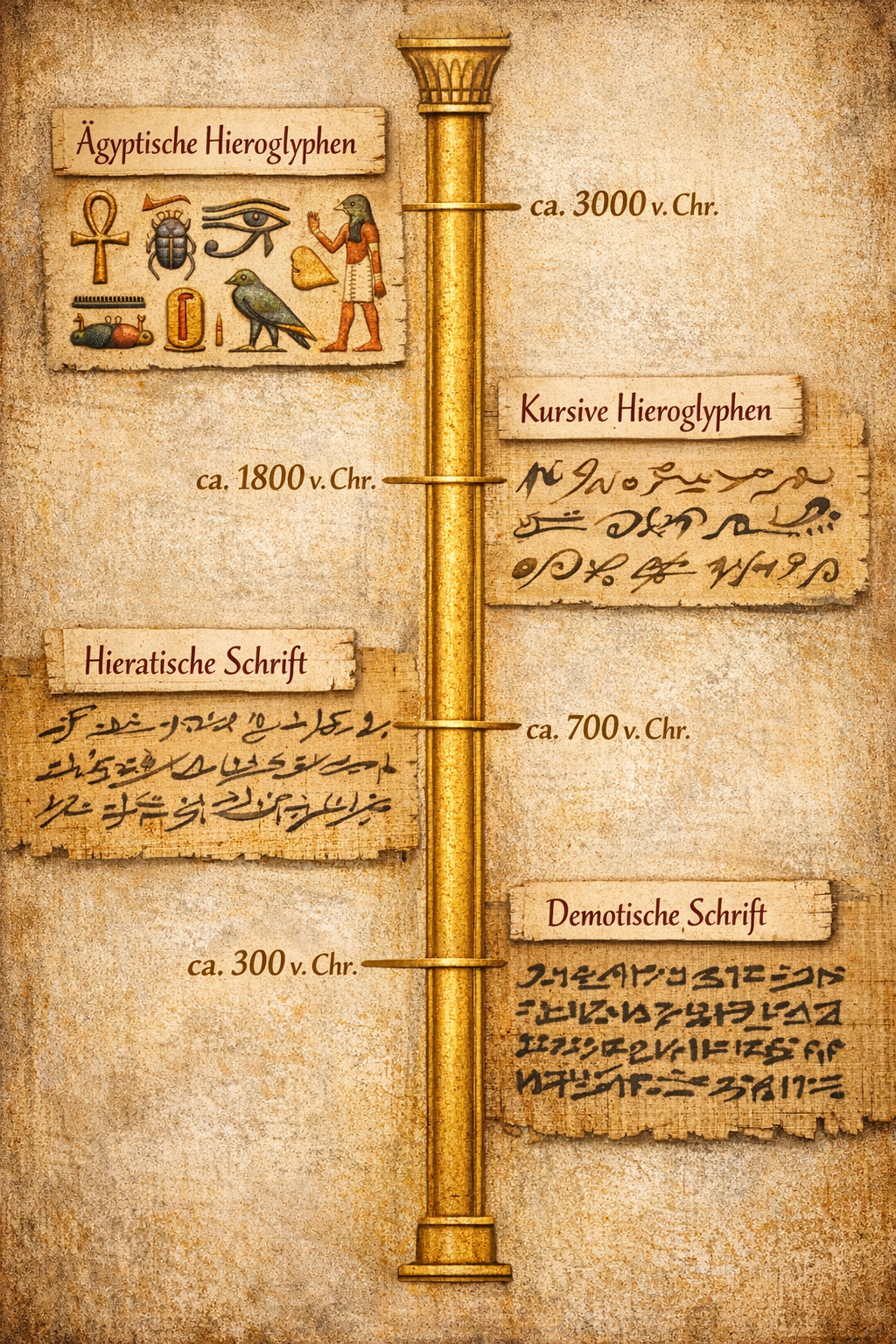
Ab 3200 v. Chr.
Hieroglyphen
„Heilige Zeichen" — ein System aus Bildern, Lautwerten und Bedeutungsträgern, in Stein gemeißelt und in leuchtenden Farben bemalt. Über drei Jahrtausende hinweg begleiten Hieroglyphen Tempel, Gräber und Königsinschriften.
Altes Ägypten
Schreiber im Dienst des Pharao
Mit Binsen, Tinte und Papyrus dokumentieren die Schreiber Ernteerträge, Bauvorhaben und göttliche Beschlüsse. Ihre Kunst war hoch angesehen — wer schreiben konnte, gehörte zu den wenigen privilegierten Stützen des Reiches.